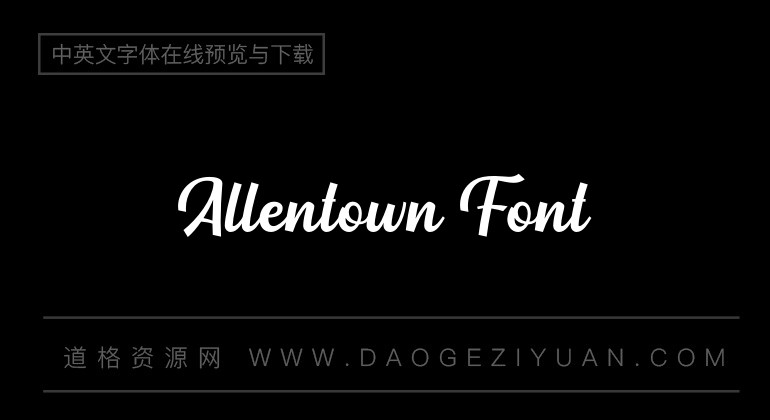
Allentown Font 是一种免费的手写字体,适用于商业和非商业用途。它的特点是线条柔和,笔画流畅,给人一种舒适自然的感觉。Allentown Font 字体包含大写和小写字母、数字、标点符号以及其他特殊字符,支持多种语言。它适合用于印刷品、标识、海报、包装、宣传册等多种设计项目中。如果你正在寻找一种免费的手写字体,Allentown Font 是一个不错的选择。内容介绍
Allentown Font是一款非常不错的手写艺术字体,具有很好的视觉感,适合于文化类的宣传设计、商业类品牌的广告和产品包装设计以及个性化文字排版等较多场景。